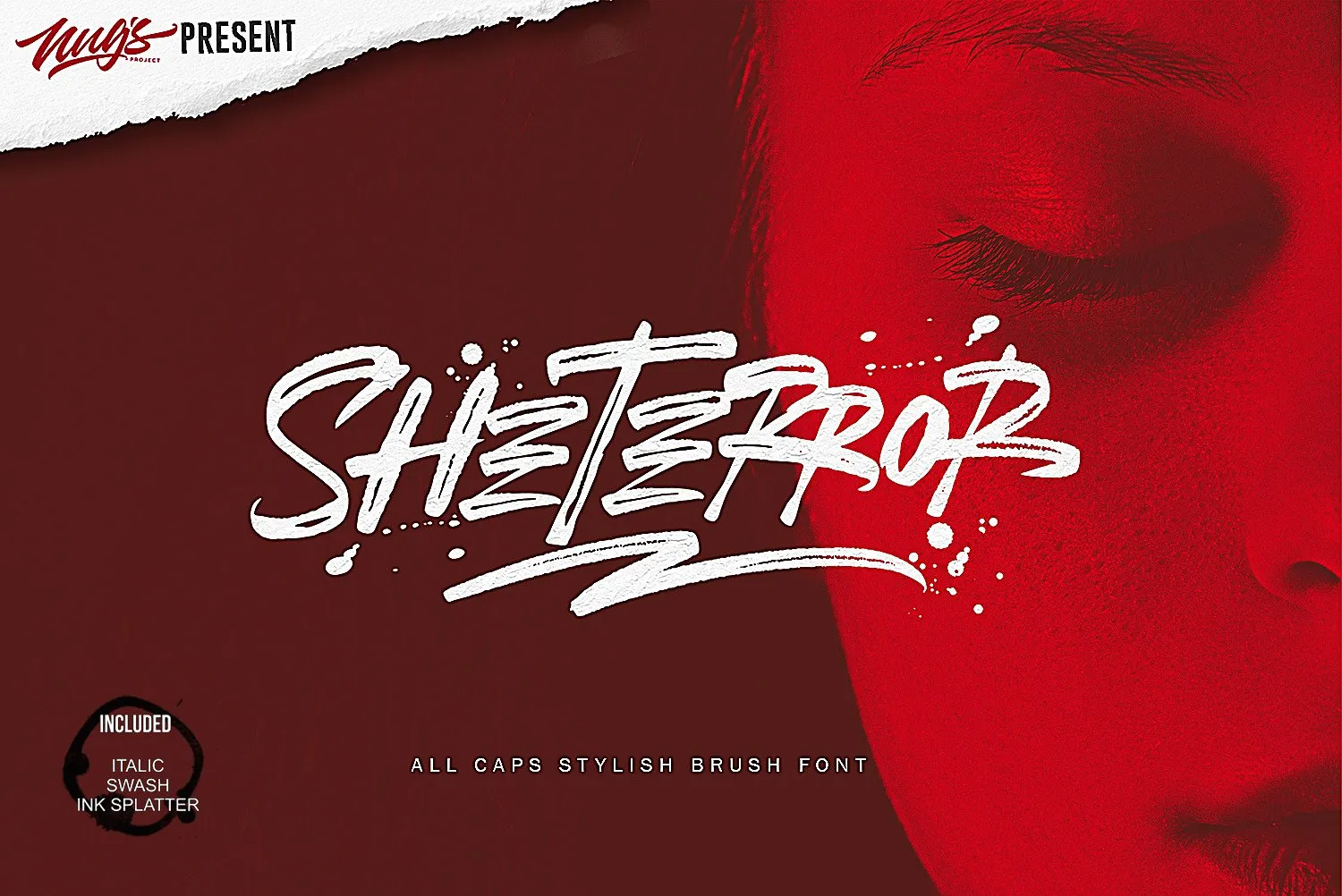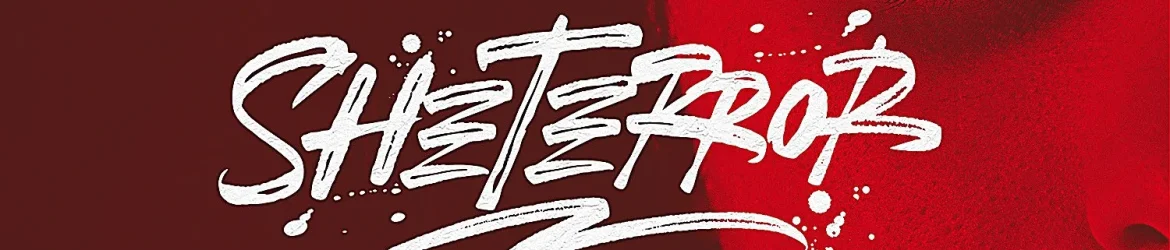
Esta é uma fonte escrita a mão usando um pincel. Ela foi projetada por NUGS para usar tanto em designs baseados em tinta ou águacolor quanto como letra fortes e esculpida à mão. Inspirado no estilo da caneta cola, esta fonte também possui essa tendência, embora possa não ser tão semelhante aos resultados originais da caneta cola, pois foi criada usando um iPad. A energia puro desta fonte pode transformar instantaneamente qualquer projeto de design gráfico em uma afirmação contundente. É perfeita para Instagram Quotes, capas de filmes e livros, blogs e quaisquer tipos de material publicitário. Seu potencial é vasto e poderoso, tornando-a uma escolha inteligente para incorporar em seu próximo projeto visual. NUGS introduz a fonte SheTerror Brush Font para inspirar designadores visuais de todas as idades.